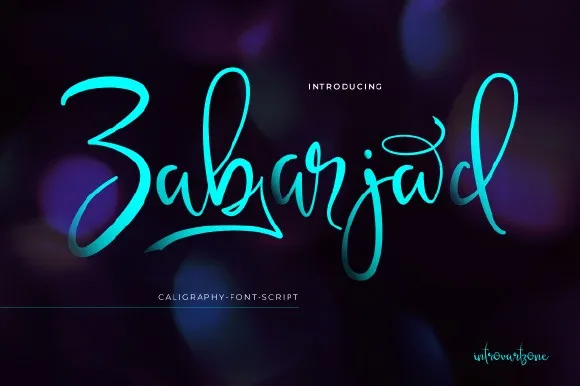
Esta é uma fonte tipo script com um estilo calligrafia, derivada das raspas feitas a mão para obter escrita natural. Ela traz os elementos principais do script de letras à mão, e se enriquecer com alternativas variadas e conjuntos estilísticos perfeitamente combinados. Introduzimos a fonte Zabarjad. Esta foi criada e compartilhada pela IntrovArtZone, um designer conhecido por produzir uma fonte que transmite um luxo e beleza únicos através da escrita à mão. Esta é uma fonte de grande valor para os projetos gráficos em variedades de mídias. Ela combina maravilhosamente com a fabricação de embalagens, as logos, etiquetas, painéis publicitários, designs de camisetas, frases de sabedoria e anúncios, tipografia, e tantos outros formatos. Zabarjad Calligraphy é ideal para tornar qualquer projeto mais elegante e sofisticado. Aproveite a sua experiência com esta fonte luxuosa, perfeita tanto na impressão digital quanto em impressão tradicional.